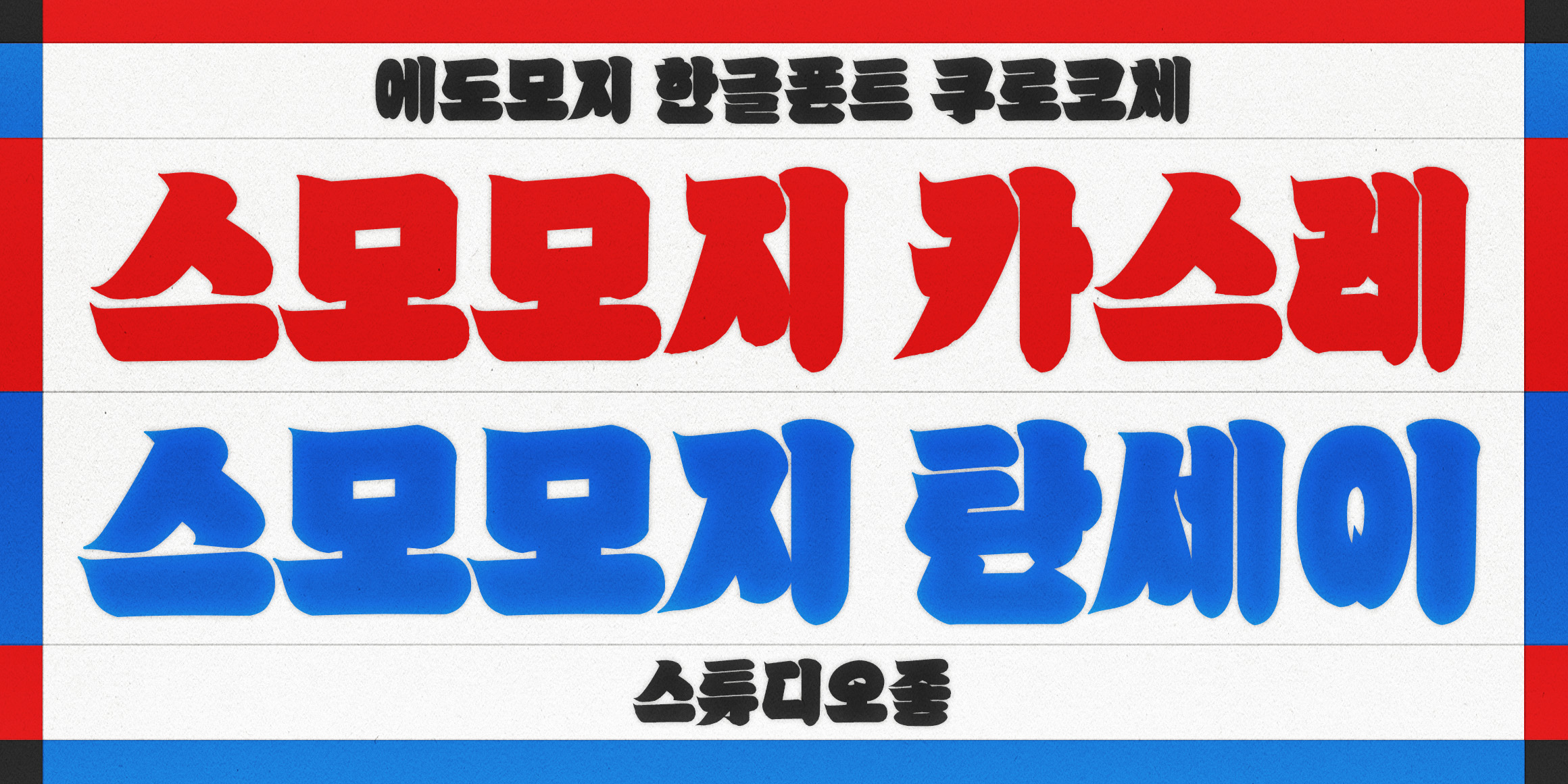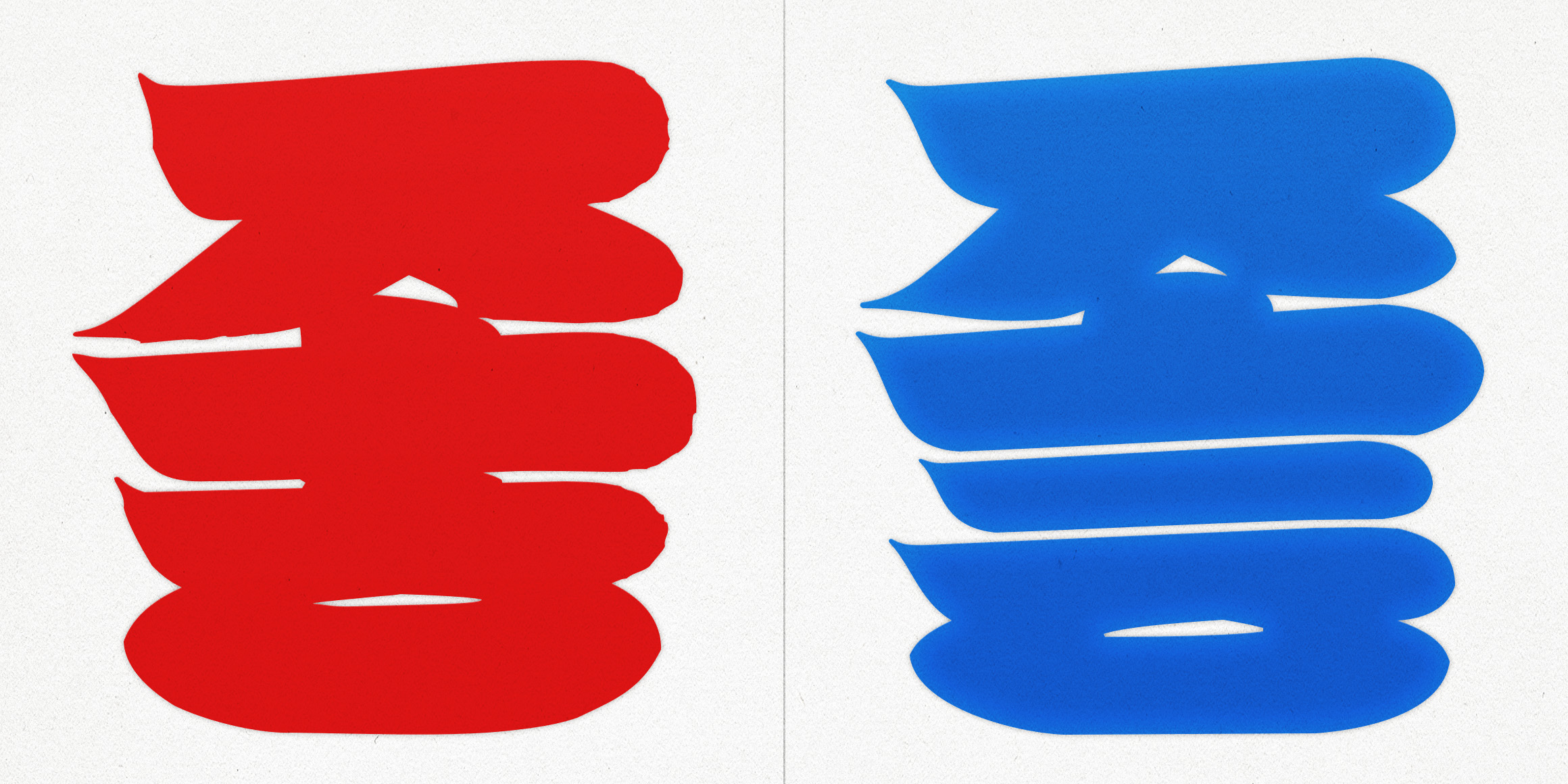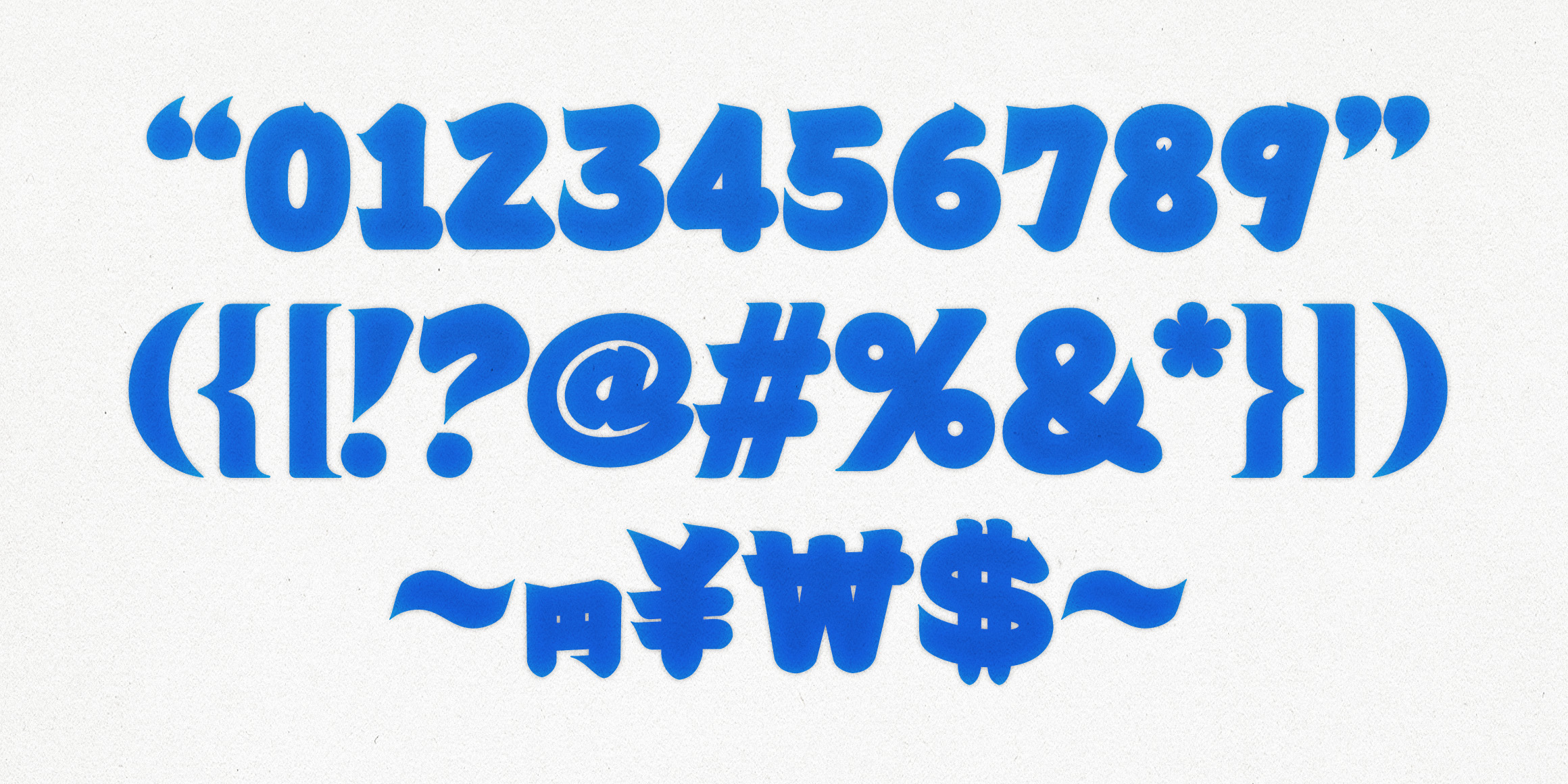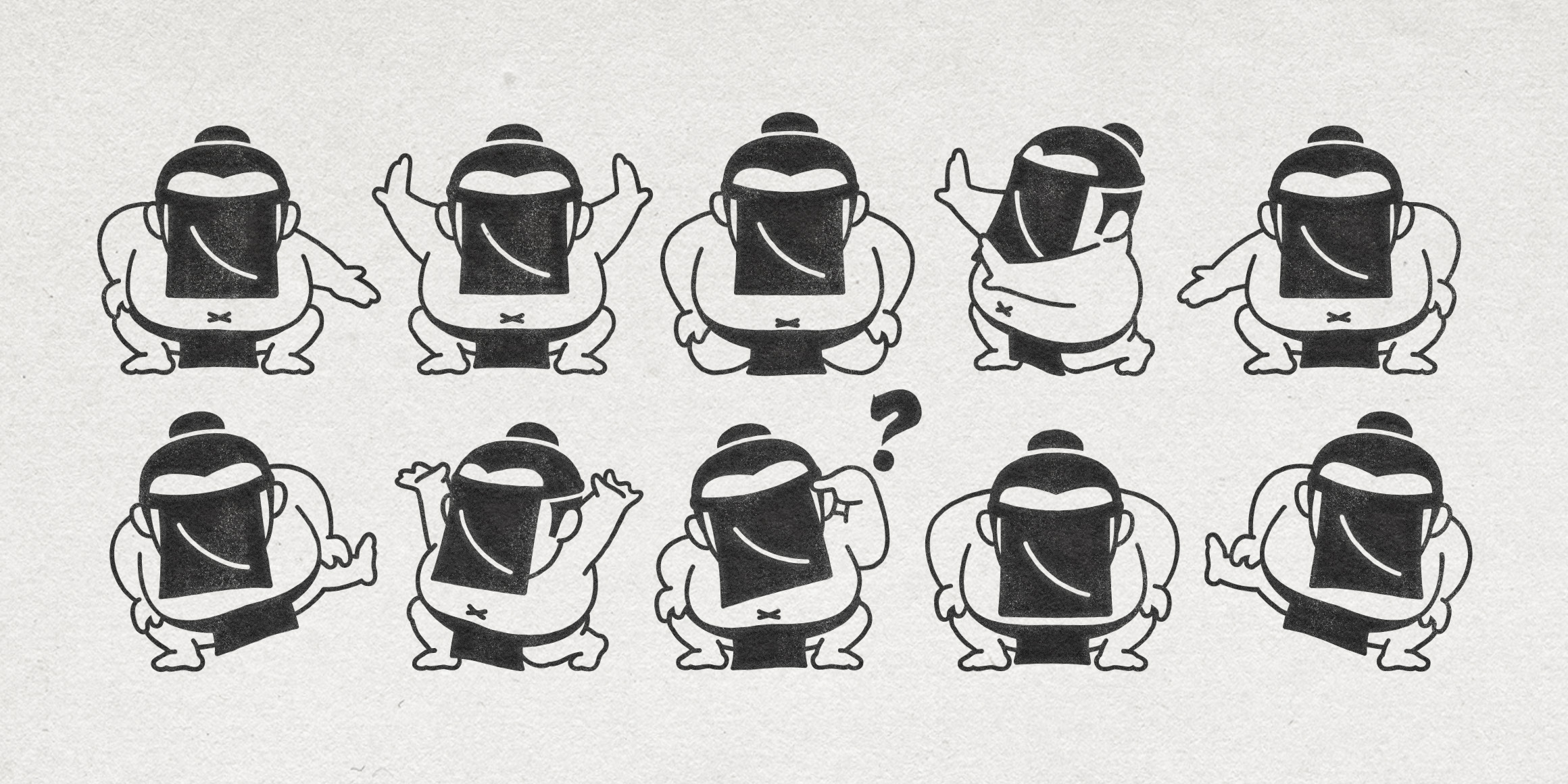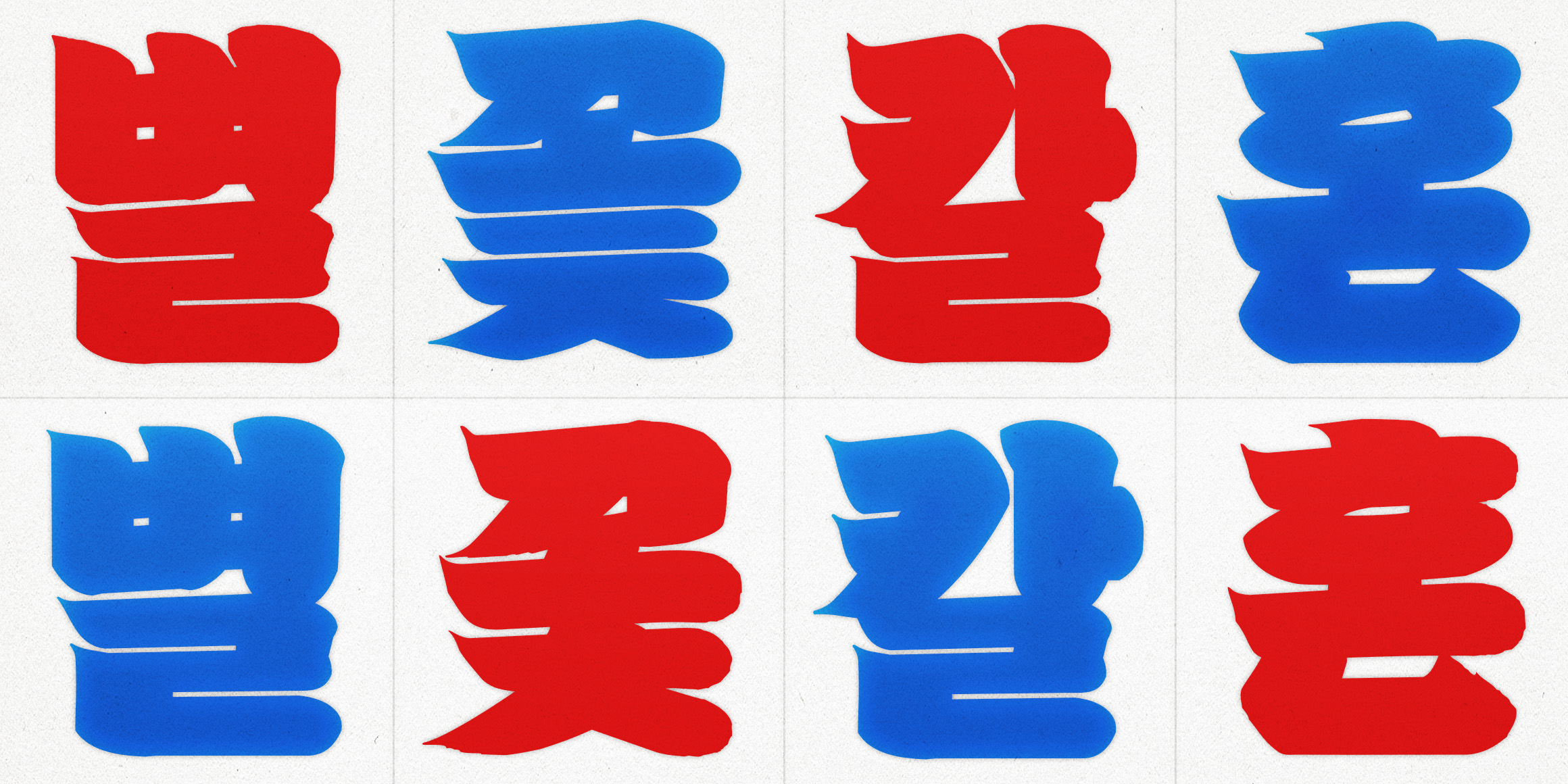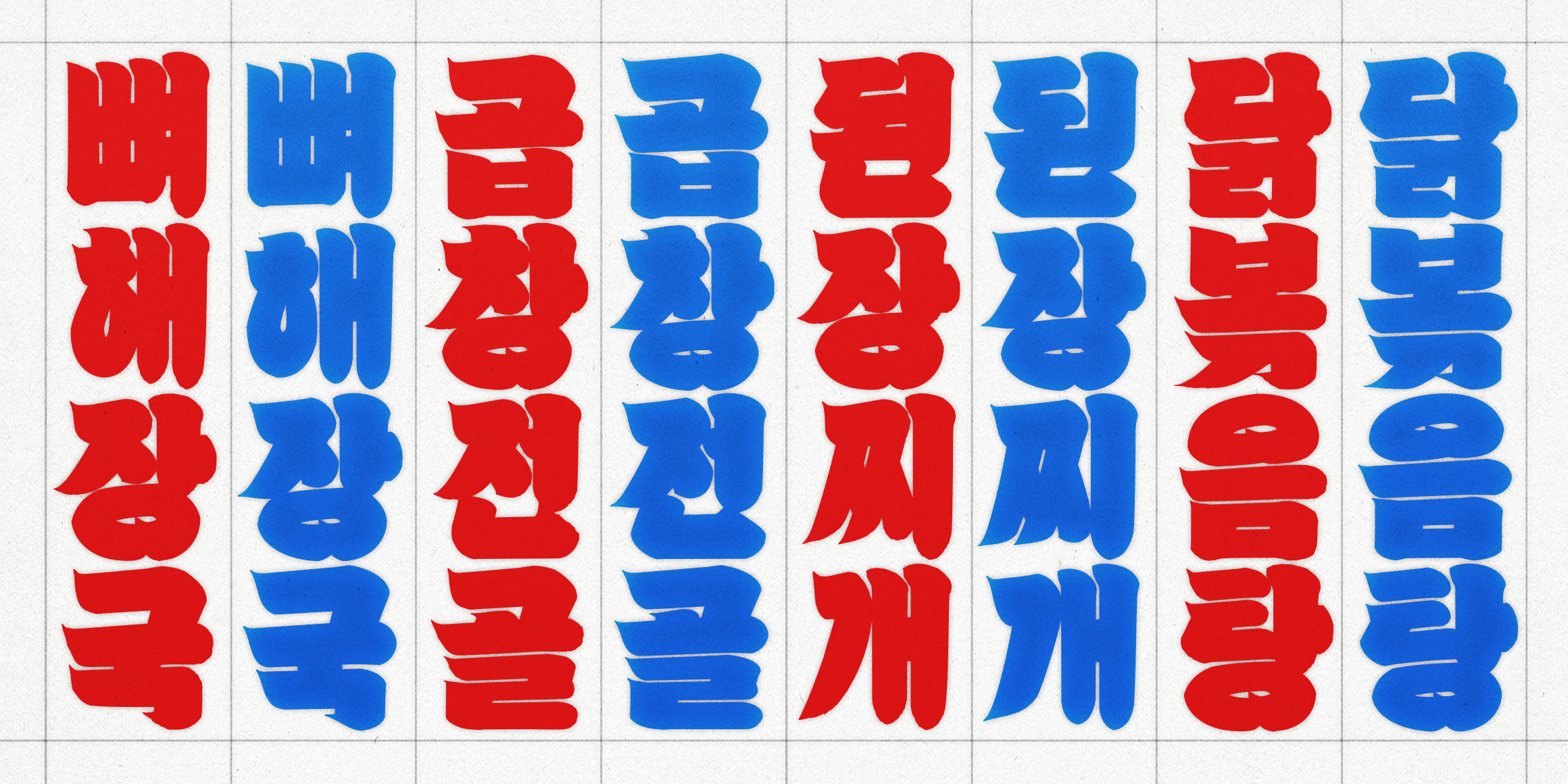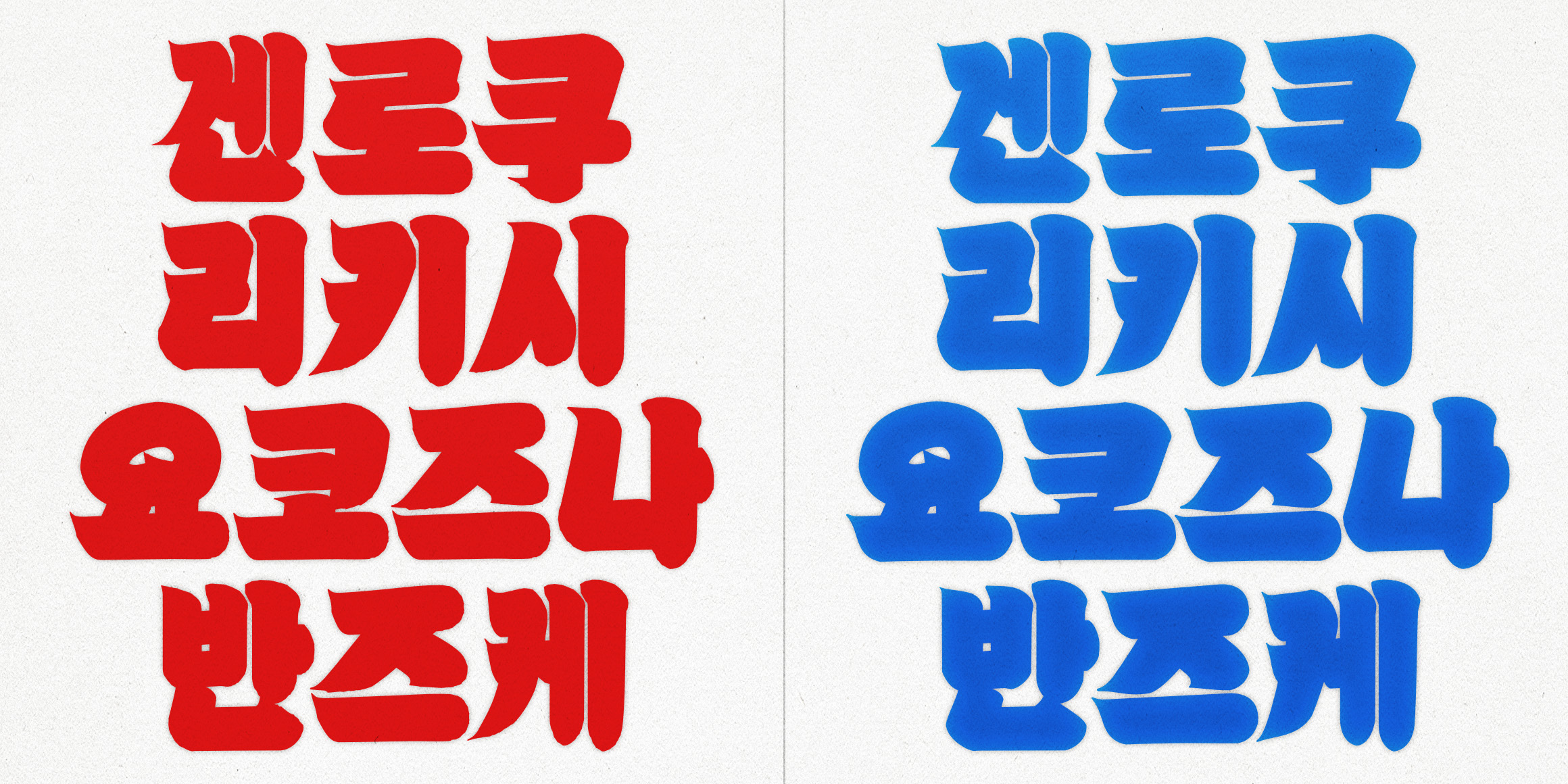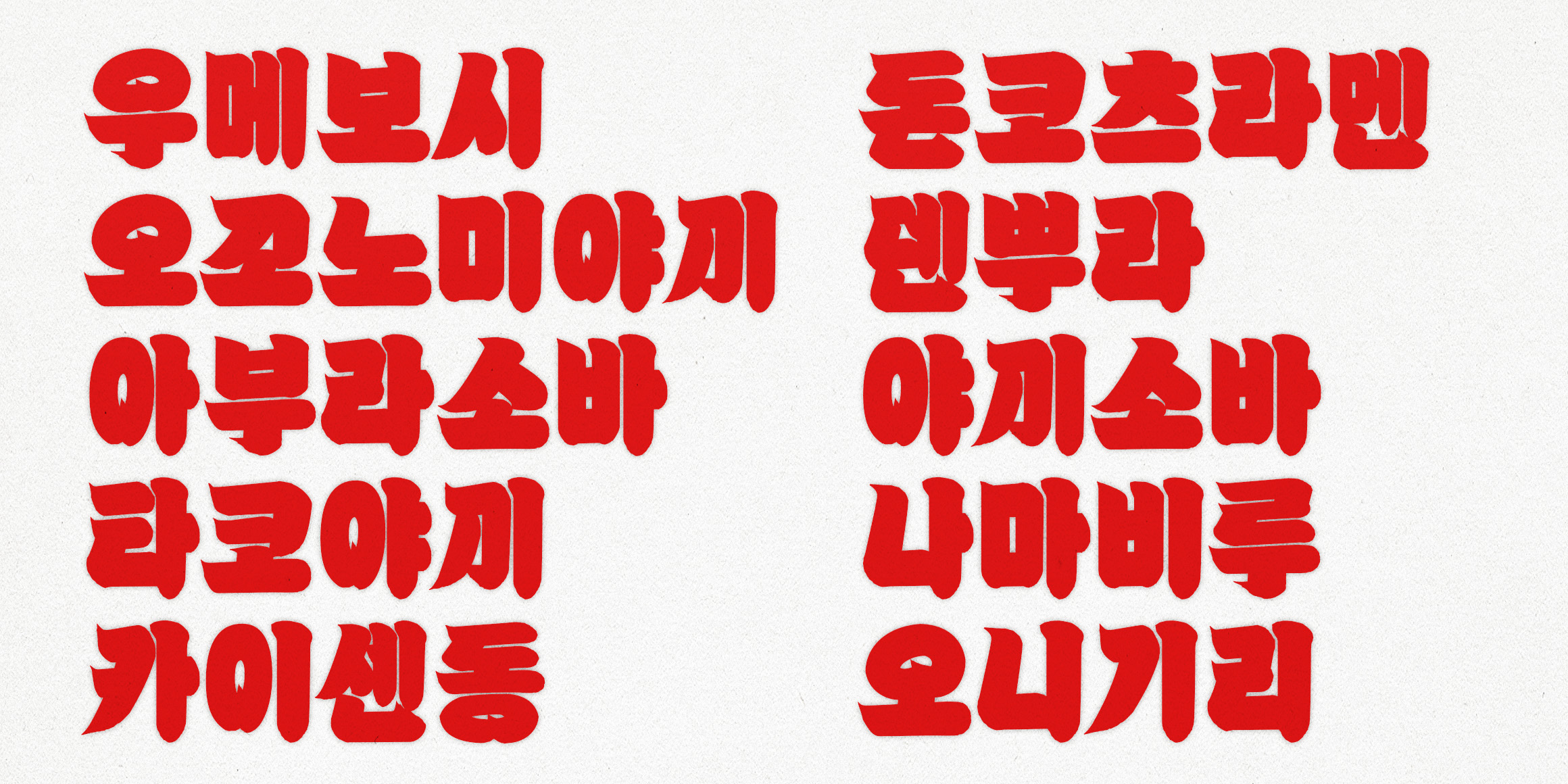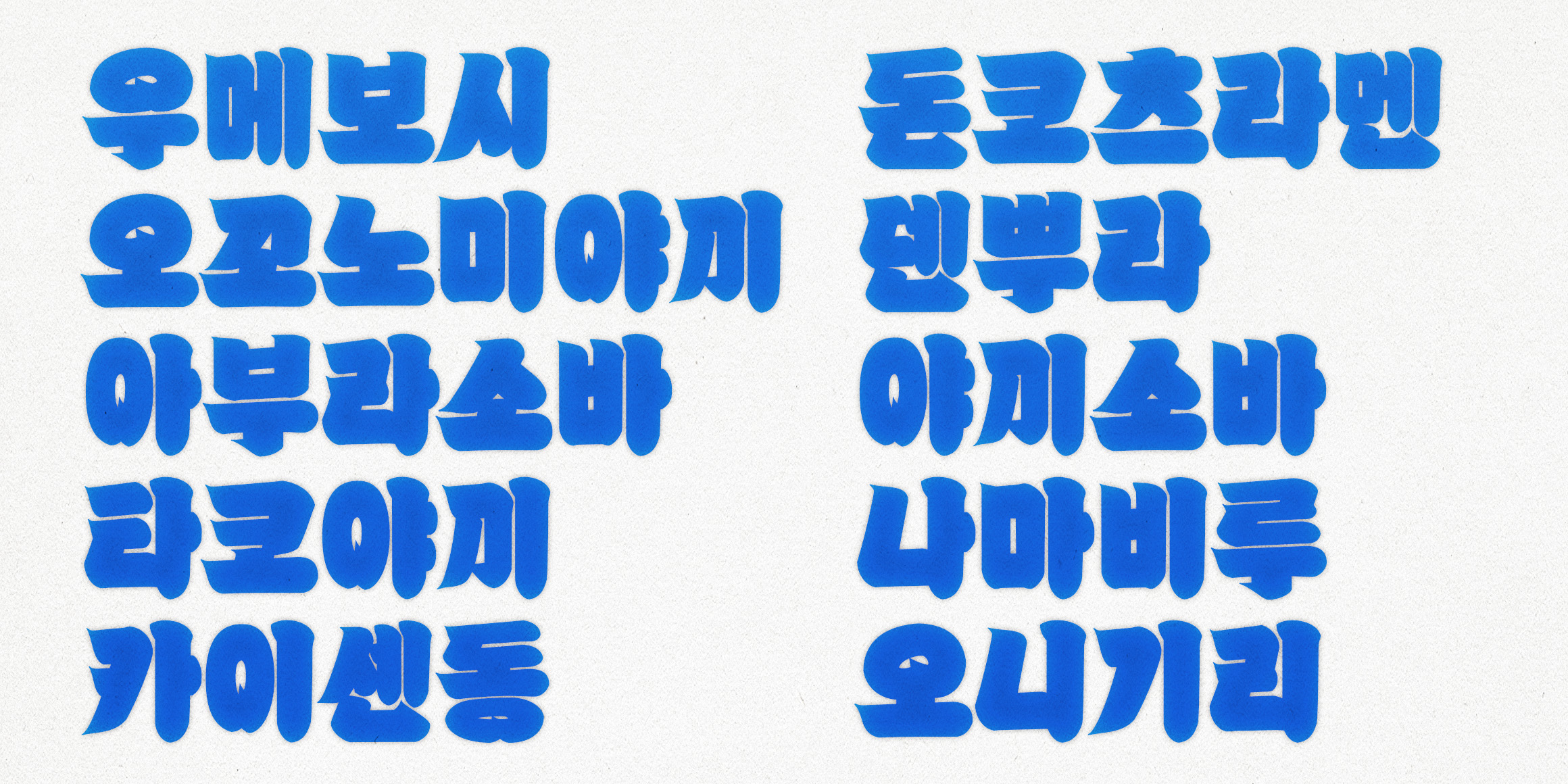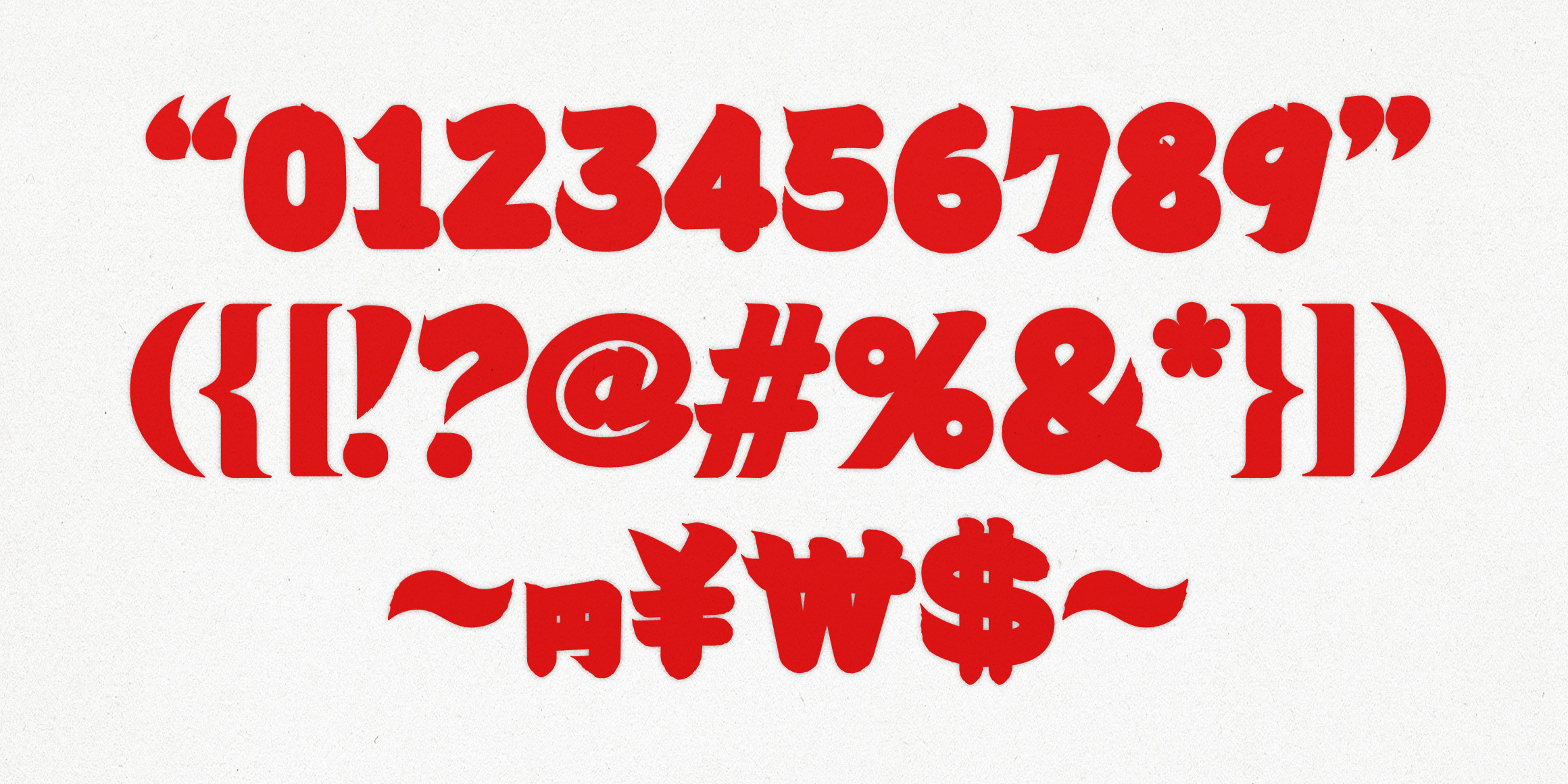
K110 쿠로코체 스모
쿠로코체 스모 1950 Kasure (카스레 カスレ : 거친, 갈필)
스모모지 원형의 날렵하고 뾰족한 갈필과 거친 붓글씨의 인상을 더욱 선명하게 살린 버전입니다.
붓이 지나가며 남기는 흔적과 거친 질감, 강한 필기감을 중심으로 스모모지 특유의 개성을 발전시켰습니다.
쿠로코체 스모 1950 Tansei (탄세이 タンセイ : 반듯한, 정돈된)
붓글씨의 흔적은 유지하면서 형태와 획을 보다 정돈된 방향으로 다듬은 버전입니다.
강한 갈필 표현을 절제하고 획의 구조를 정리하며 무게감을 더해, 기존 스모모지의 인상을 유지하면서도 보다 다양한 환경에서 활용할 수 있도록 제작했습니다.
[K110 쿠로코체 스모]는 일본의 역사 깊은 글자체인 에도모지(江戸文字), 그중에서도 스모모지(寄席文字) 스타일에서 영감을 받은 한글 서체입니다.
기존 한글 서체가 2,780자로 구성된 데 비해, 이 서체는 일본어로 발음 가능한 글자들과, 범용성을 위해 추가된 글자들을 포함하여 1950자로 구성되어 있습니다.
없는 글자가 입력될 경우 쿠로코가 등장해 기존에 없던 독특한 타이핑 경험을 선사합니다.